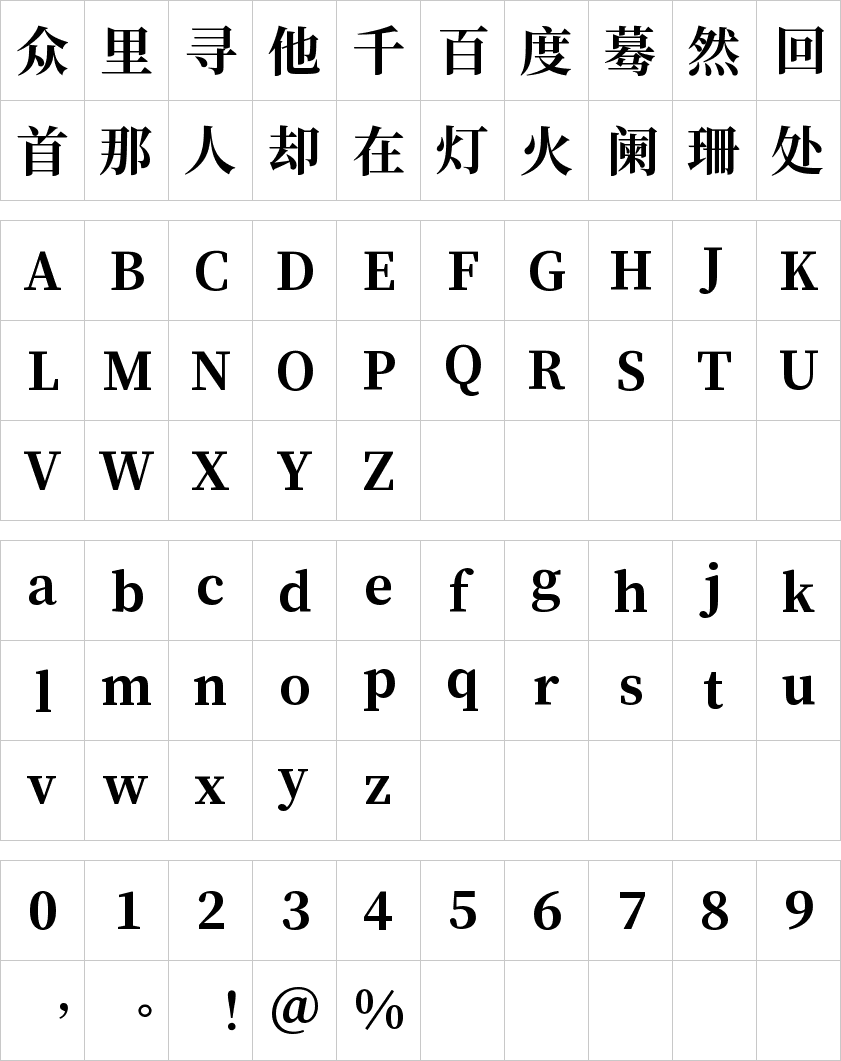
昭源宋體
昭源宋体(Chiron Sung HK)是与昭源黑体/昭源黑体Pro对应的免费开源宋体字型,两者可以互相配搭使用。本字体收字量大、具现代感,而且字重丰富,用于荧幕显示、纸本印刷皆宜。
昭源宋体是从Adobe 和Google 共同开发的 思源宋体香港版(Source Han Serif – Traditional Chinese, Hong Kong)修改而成。「思源宋体香港」以中文界面咨询委员会(中咨会)在2016 年公布的《香港电脑汉字参考字形》为字形依据,但由于该文件所拟定的某些字样面貌以印刷字而言在香港以至其他繁体中文地区并不常见,使用者或会因为字形陌生、需时适应而影响阅读节奏。又因「参考字形」的总体原则是宋体(印刷体)与楷体(手写体)字形规律一致并以楷书写法为准,导致好些本来只用于楷书或在以往印刷体(即使是采现代笔形者,无论宋体还是黑体)中较为罕见的部件形态移植到印刷体,令某些字的笔形或结构对一般人来说可能会显得奇怪。
因应以上情况,「昭源宋体」以「思源宋体香港」为基础,检视选定范围内的字样,比较着重一字用于印刷时的显示效果。字体会参考大众日常生活所见的「事实标准」调整字形,冀能提供一套平衡标准字形和印刷体惯用笔形的现代笔形风格宋体字型。